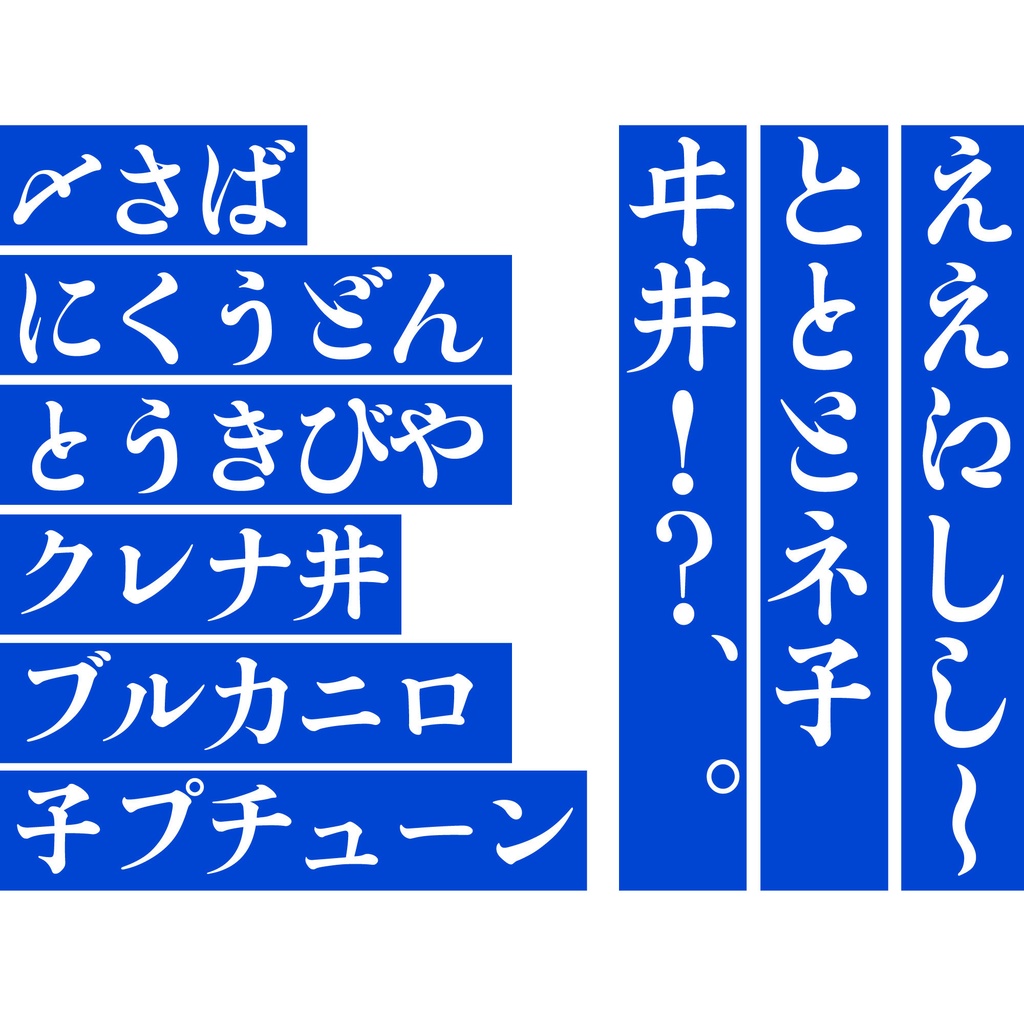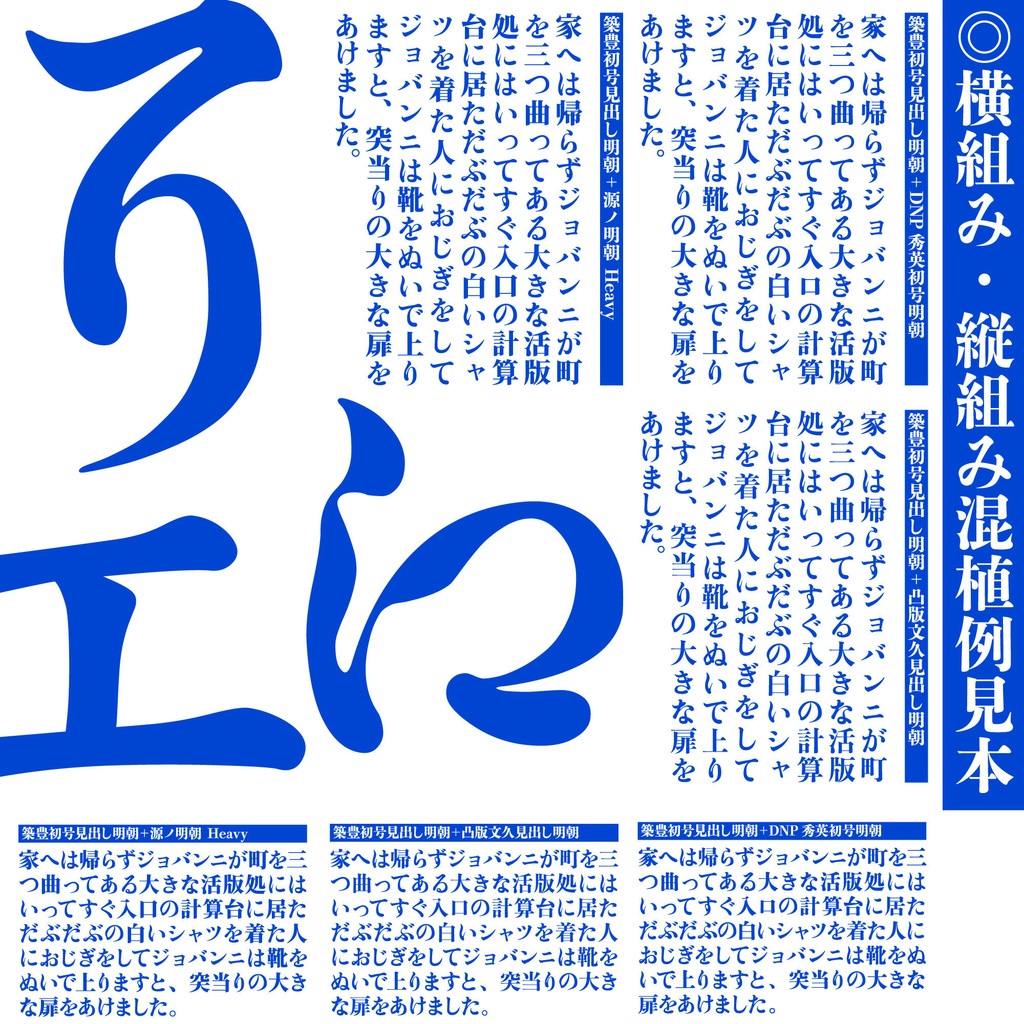
【フリーフォント】築豊初号見出しかな│見出し用オールドスタイルかな書体
■書体概要 築豊初号見出しかな(つくほうしょごうみだしかな)は金属活字の築地初号やそれから派生した民友社初号明朝、写植書体のかな民友明朝、大蘭明朝参考に制作した見出し用かな書体です。 豊かな表情のある骨格や文字と多少不揃いな雰囲気を残すことを意識しています。 また、OpenType機能のStylistic Setを使うことができ、一部字形を旧いものと現代で一般的なものに切り替えが可能となっております。(ss01~02までを収録) 等幅フォントのため、ご自身で適切なカーニングを行うとよりきれいに見えるでしょう。 ■収録字形 ひらがな、カタカナ、約物、一部記号の全311グリフが収録されています。 詳しくは、同梱の画像に掲載しています。 ■ご利用にあたり 商用・個人利用可能です。また、著作権は放棄しておりません。 個人的なフォントの改変は自由ですが、派生フォントの配布はお控えください。 フォントファイル単体の二次配布は禁止です。 このフォントを使用したことによるトラブルや損害に関しては一切の責任を持ちません。 ■ご不明な点がありましたら Twitter(@iose_sakana)のDMまでご連絡お願いします。 2023/02/06 Ver1.000 公開 Copyright (c) 2023 Typographish All Rights Reserved.